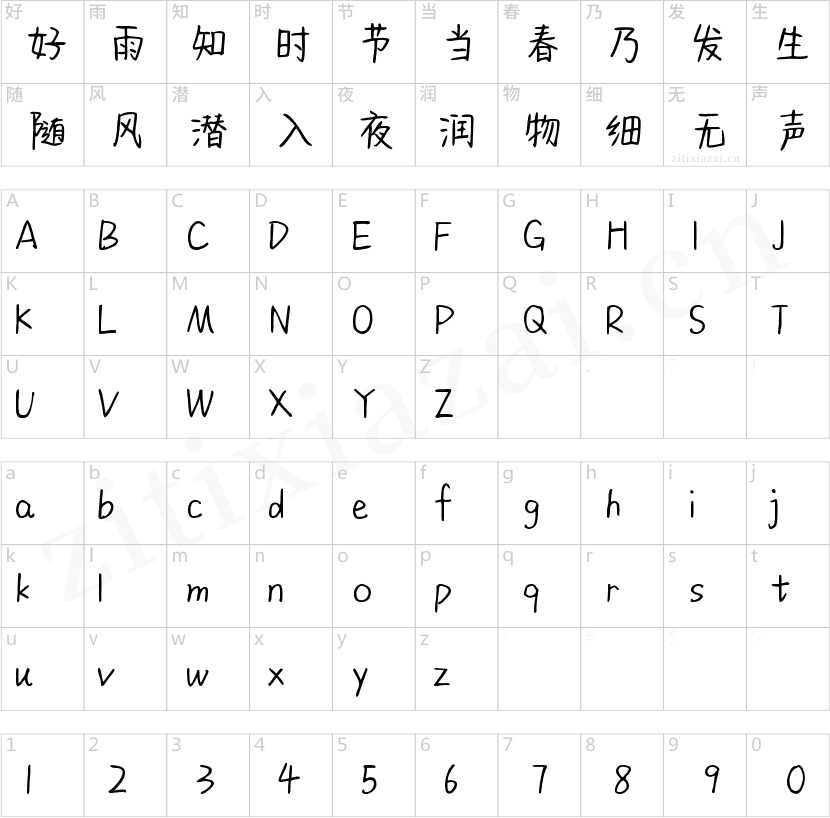
Aa甜瘾温喉
Aa甜瘾温喉字体
Aa甜瘾温喉是一款非常具有艺术性的字体,它的设计灵感来源于对古典艺术的研究,同时又融入了现代字体设计的元素。字形优美,笔画粗细变化自然,给人以大气、典雅的感觉。Aa甜瘾温喉是一款既传统又现代的字体,它的设计充满艺术感,美观大方,实用性也非常强。无论是对于设计师还是对于普通读者来说,都是一种非常不错的字体选择。Aa甜瘾温喉适合用于具有艺术感的场合,比如海报、宣传单张、书籍封面等。由于其字形流畅且具有动态感,也适合用于大量的文本排版,如报纸、杂志等。